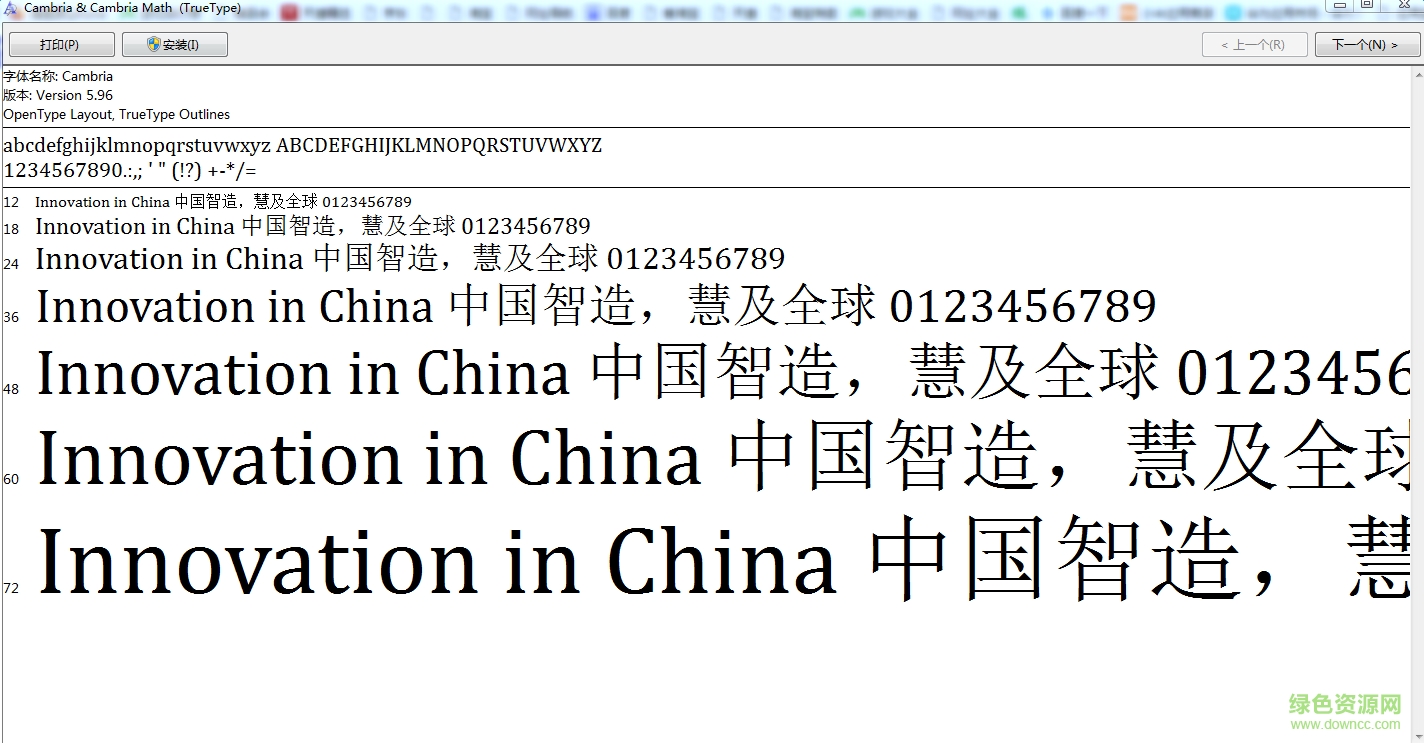
cambria math字體是微軟辦公軟件中常見的一款現(xiàn)代襯線字體,該字體力度和變化恰到好處,表現(xiàn)力十分豐富,需要的朋友快來(lái)綠色資源網(wǎng)下載吧!
serif字體容易識(shí)別,它強(qiáng)調(diào)了每個(gè)字母筆畫的開始和結(jié)束,因此易讀性比較高,
sans serif字體則比較醒目。在整文閱讀的情況下,適合使用serif字體進(jìn)行排版,易于換行閱讀的識(shí)別性,避免發(fā)生行間的閱讀錯(cuò)誤。